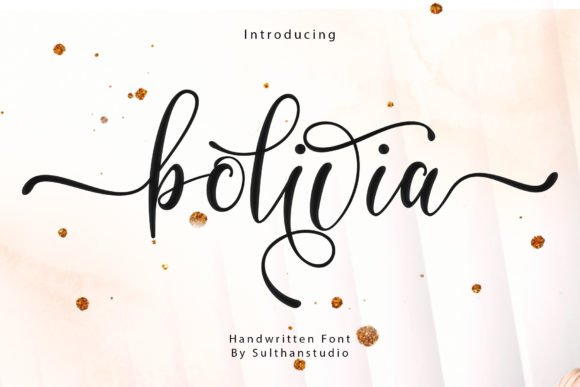
Creativefabrica Bolivia Font
[Creativefabrica] Bolivia Font
Bolivia - это уникальный и элегантный рукописный шрифт.
Он прекрасно смотрится на различных дизайнах, требующих индивидуального стиля, таких как свадебные приглашения, благодарственные открытки, свадьбы, поздравительные открытки, логотипы и так далее.